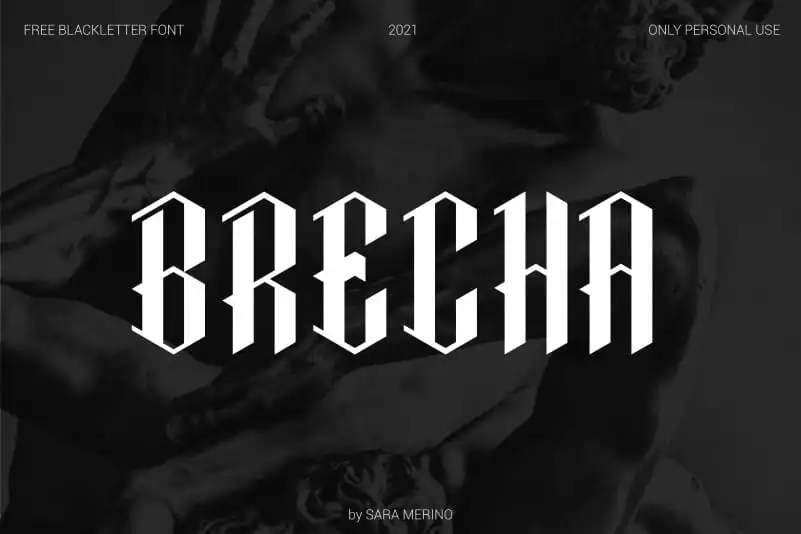
Brecha Blackletter Display Font
A Brecha Blackletter Display Font é uma tipografia de letra gótica que oferece um estilo moderno, embora seus traços sejam marcados por ângulos agudos e formas retas. Esta fonte é perfeita para aplicar em posters, títulos editoriais, capas de livros ou qualquer design que deseje exibir personalidade. Seu formato imponente a torna uma escolha ótima para expressar ideias fortes e ressaltar elementos importantes em sua próxima produção visual. A Brecha Blackletter Display Font é perfeita para quem busca uma fonte de letra gótica que se destaca não apenas pela sua aparência elegante, mas também por seu poder de personalização. Seja você um designer gráfico profissional ou alguém iniciando no campo da design editorial, esta fonte oferece o ideal para expressar seus ideais e criar um design único.